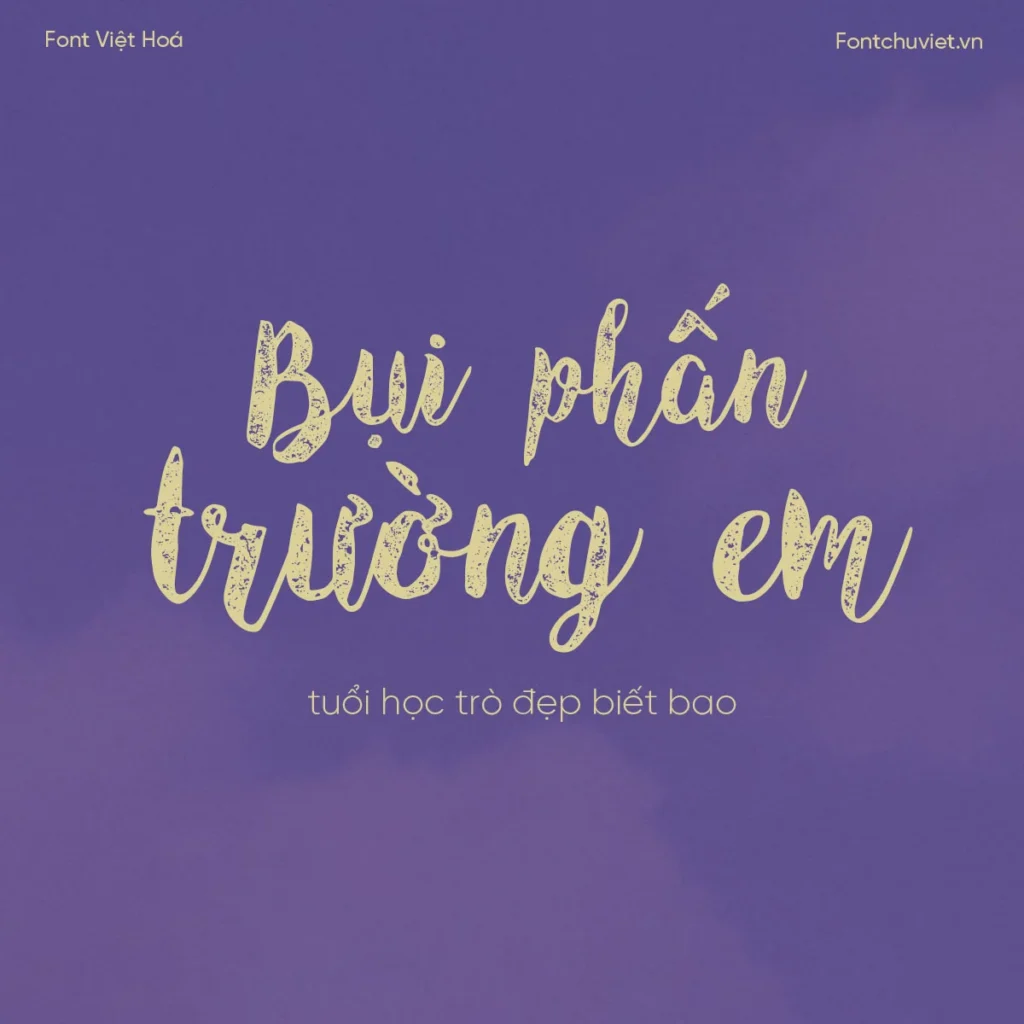
Font VL Angeline Vintage – Font Việt hoá là một trong những lựa chọn hàng đầu cho các nhà thiết kế đang tìm kiếm phong cách viết tay độc đáo. Bởi vì font được thiết kế tạo các lổ nhỏ li ti lên trên, mang lại cảm giác giống style viết phấn.
Font VL Angeline Vintage – Font Việt hoá: Ưu Điểm Và Ứng Dụng
Font này lý tưởng cho các thiết kế mùa tự trường, bởi nó mang lại cảm giác ấm áp và thân mật. Bên cạnh đó, Font VL Angeline Vintage – Font Việt hoá cũng có thể được sử dụng trong nhiều dự án khác như thiết kế card, thiệp mời, và thậm chí là logo.
Các Đặc Điểm Nổi Bật Của Font VL Angeline Vintage – Font Việt hoá
Thiết Kế Độc Đáo
Font VL Angeline Vintage – Font Việt hoá có thiết kế giống style viết phấn, với các lổ nhỏ li ti lên trên. Điều này mang lại cảm giác độc đáo và thú vị cho các thiết kế.
Ứng Dụng Phong Phú
Font này có thể được sử dụng trong nhiều dự án khác nhau, từ thiết kế mùa tự trường đến thiết kế card, thiệp mời, và logo.
Sử Dụng Font VL Angeline Vintage – Font Việt hoá Trong Thiết Kế
Lợi Ích Của Font VL Angeline Vintage – Font Việt hoá
- Mang lại cảm giác ấm áp và thân mật cho các thiết kế
- Độc đáo và thú vị, giúp các thiết kế của bạn nổi bật
- Ứng dụng phong phú, có thể được sử dụng trong nhiều dự án khác nhau
Kết Luận
Font VL Angeline Vintage – Font Việt hoá là một lựa chọn hoàn hảo cho các nhà thiết kế đang tìm kiếm phong cách viết tay độc đáo. Với thiết kế giống style viết phấn và ứng dụng phong phú, font này có thể giúp các thiết kế của bạn trở nên ấm áp, thân mật, và độc đáo. Hãy tải xuống và trải nghiệm Font VL Angeline Vintage – Font Việt hoá ngay hôm nay!